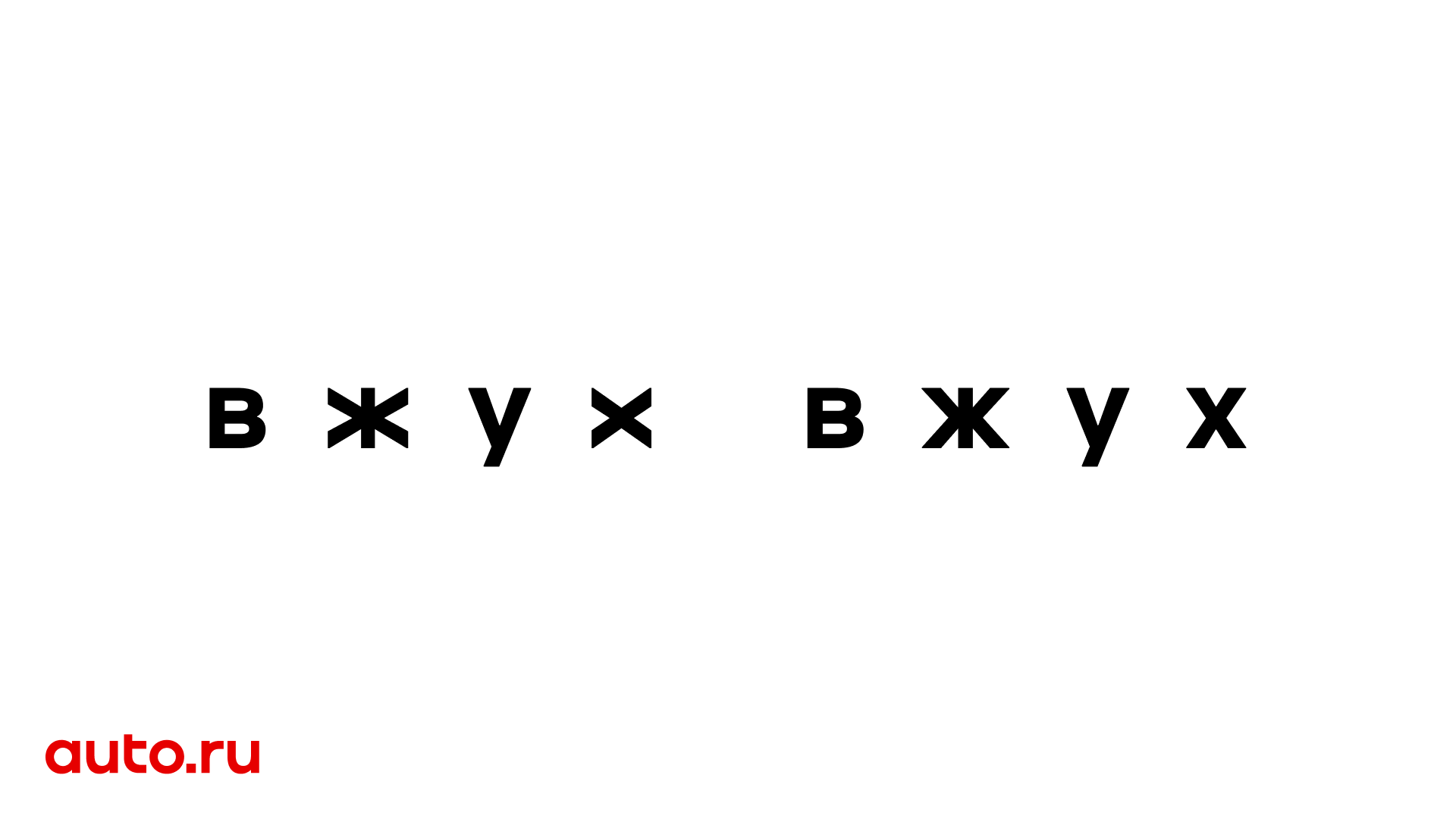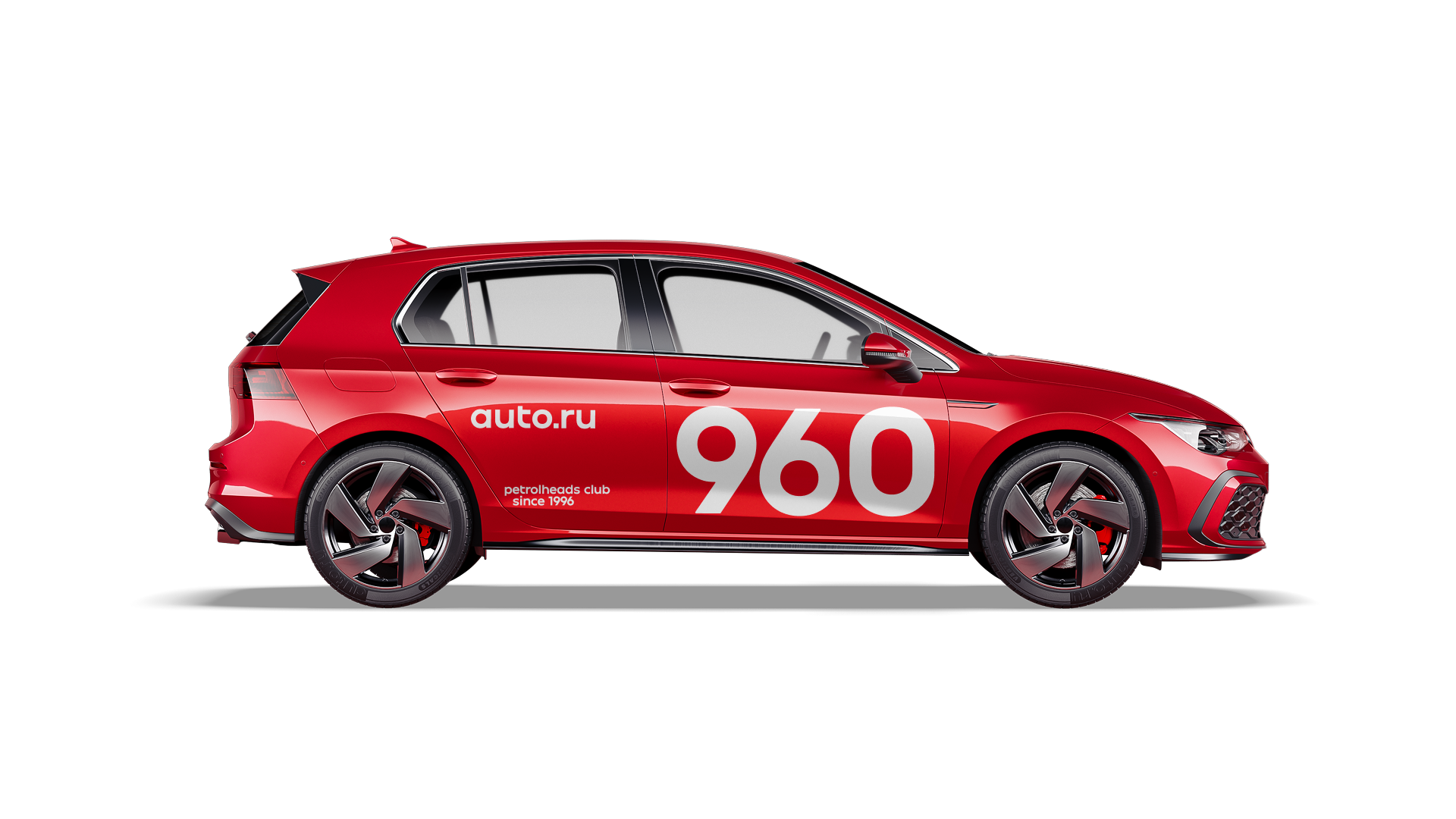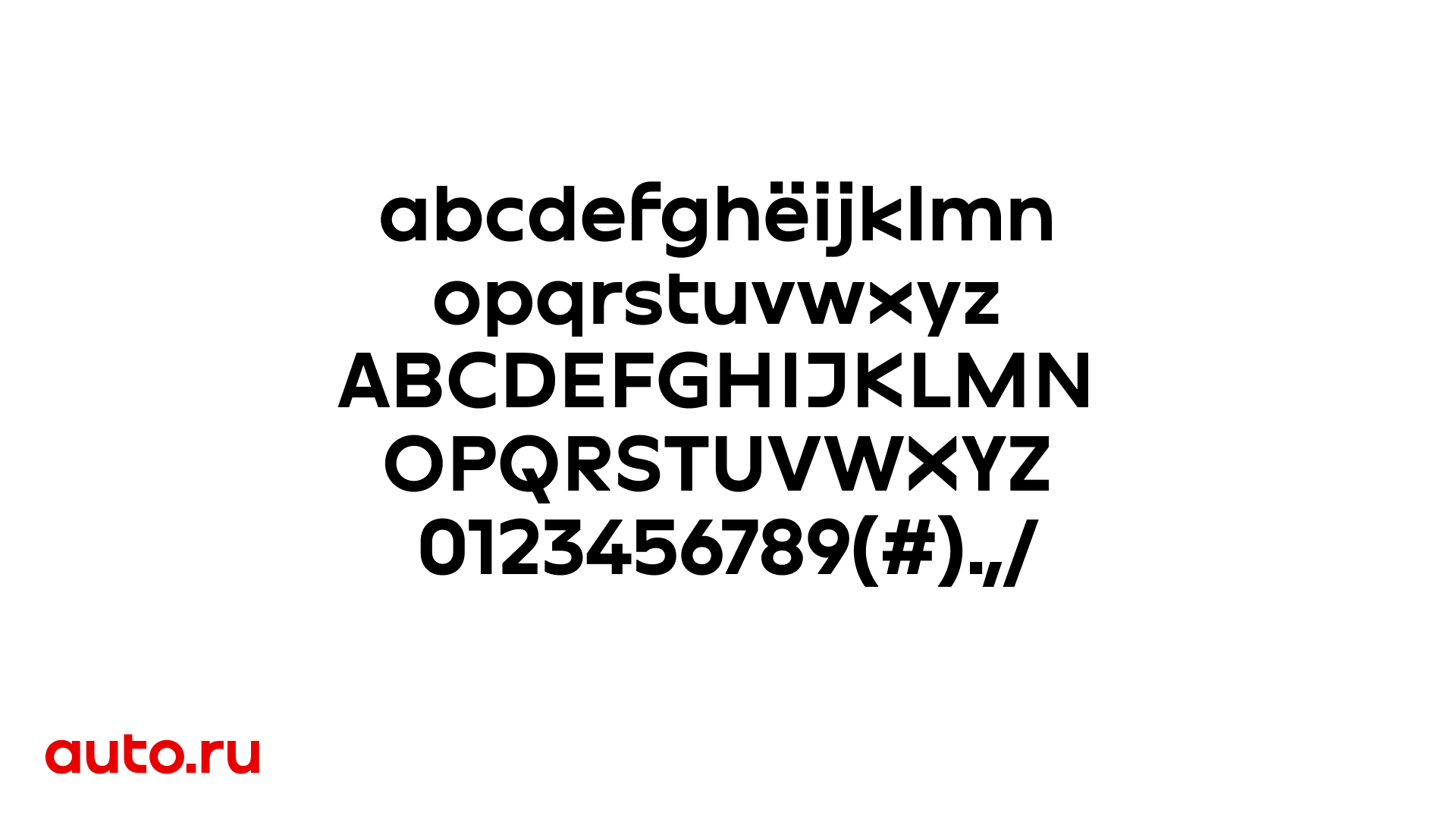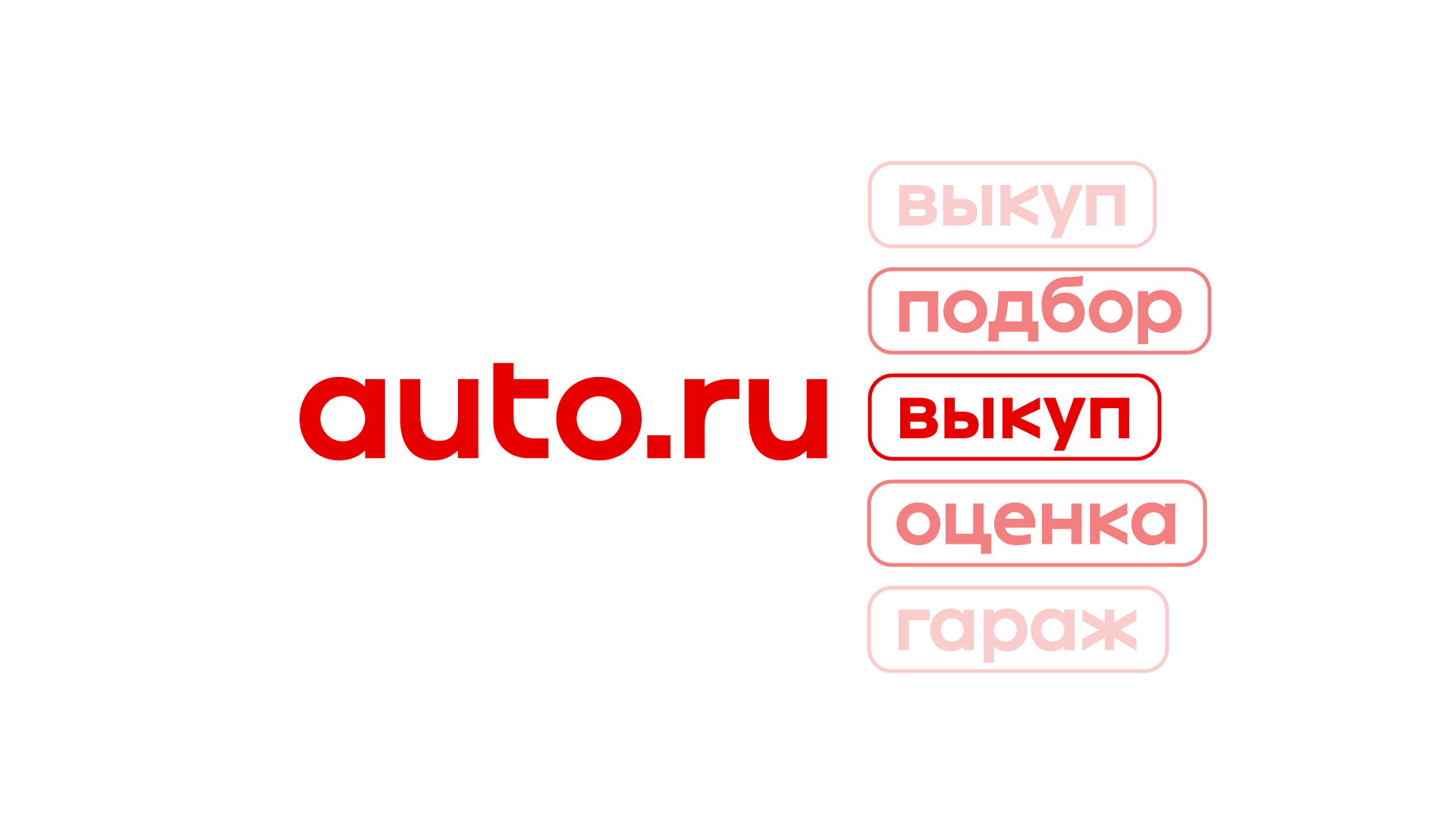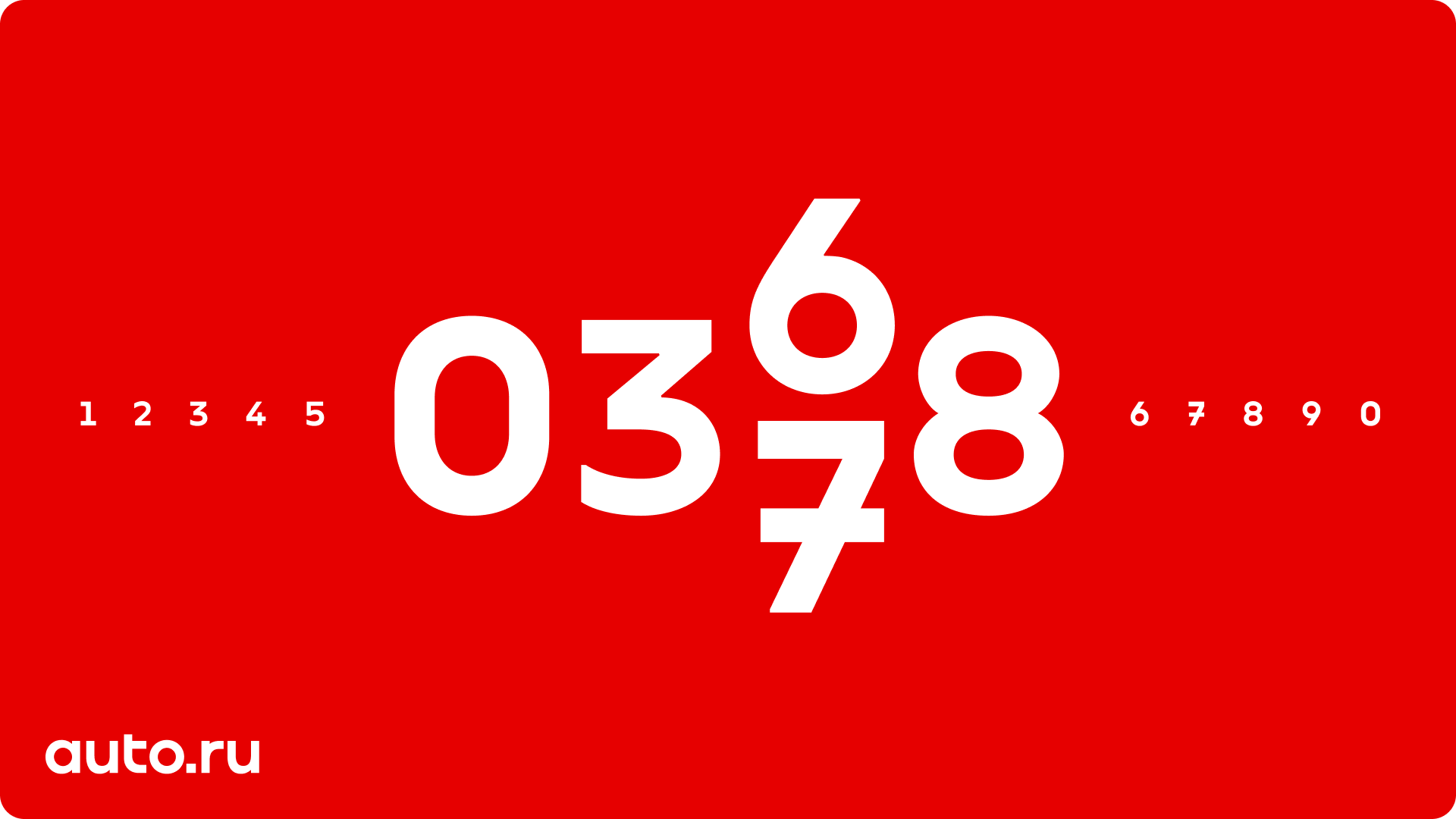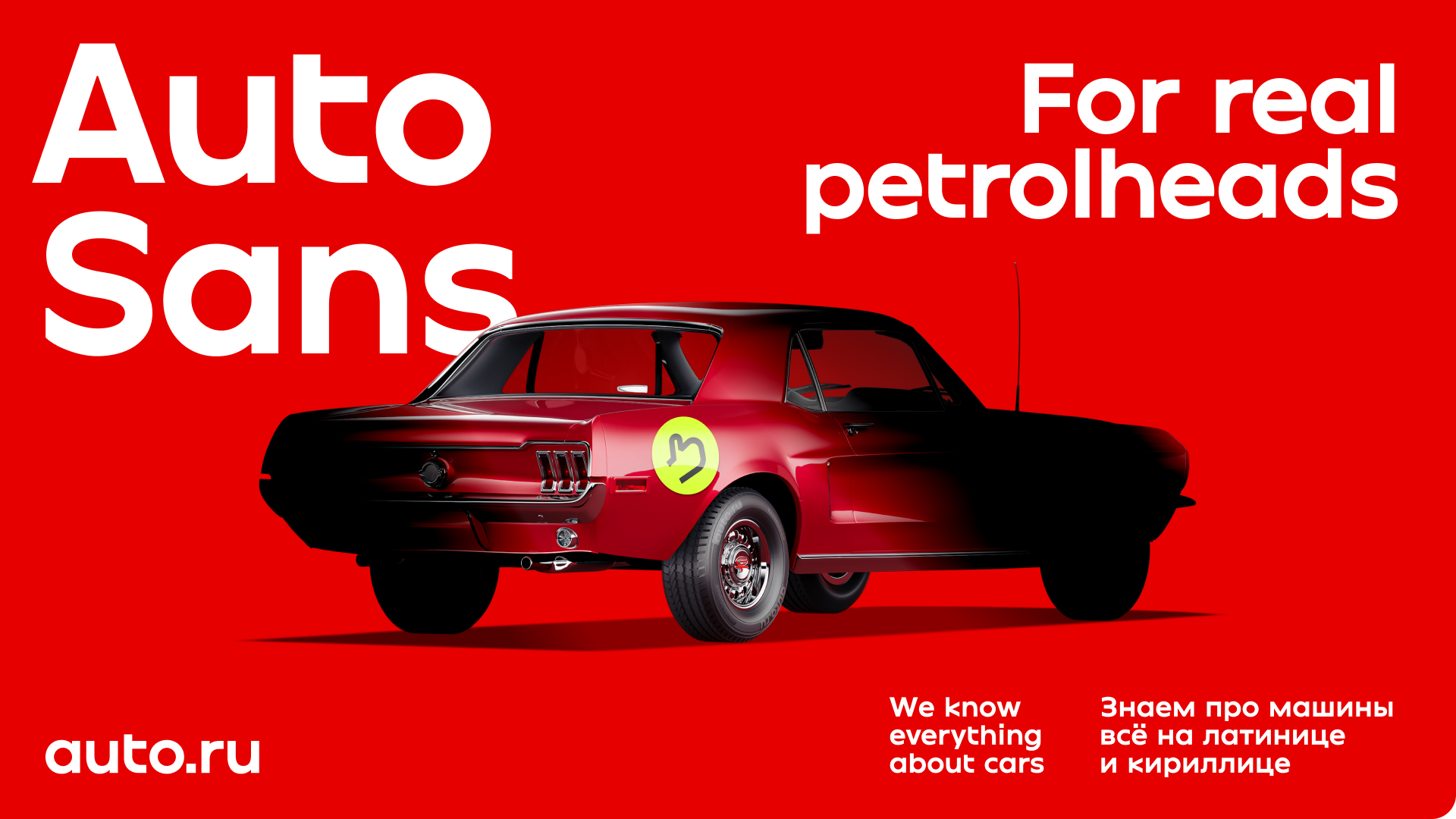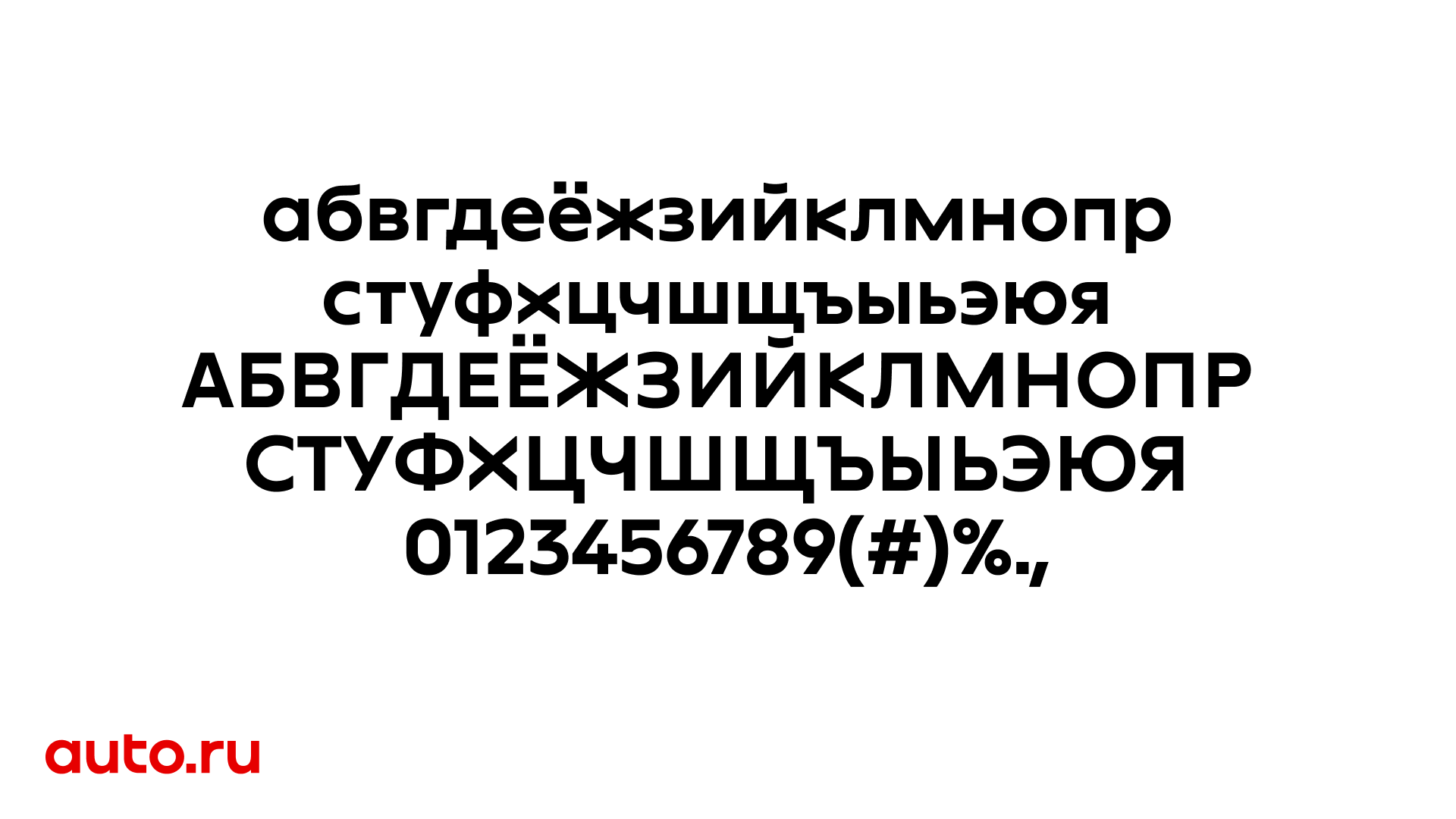
Шрифт Авто. ру
Специально для обновленного логотипа Авто. ру мы создали кастомный шрифт.
Это нужно было сделать, так как, помимо основного бренда, есть множество сервисов и саб-брендов, каждому из которых нужна своя версия.
Важно было при этом, чтобы логотип гармонично сочетался с нашим основным шрифтом Yandex Geo.
Так же как в логотипе в новом шрифте есть броские, запоминающиеся детали, но он не выглядит чрезмерно декоративным.
Например, мы решили использовать строго вертикальные срезы в буквах, даже тех, в которых обычно этого не делается (в кириллических Ж, К, Х).